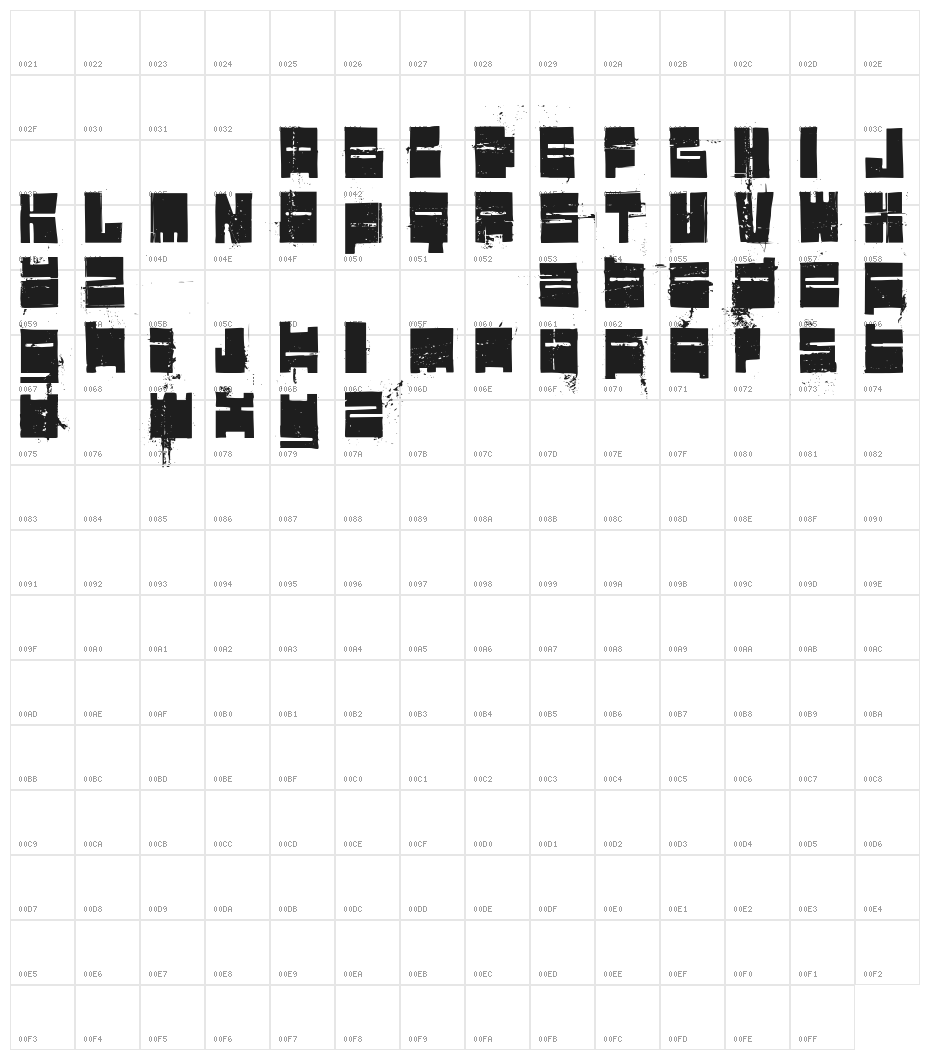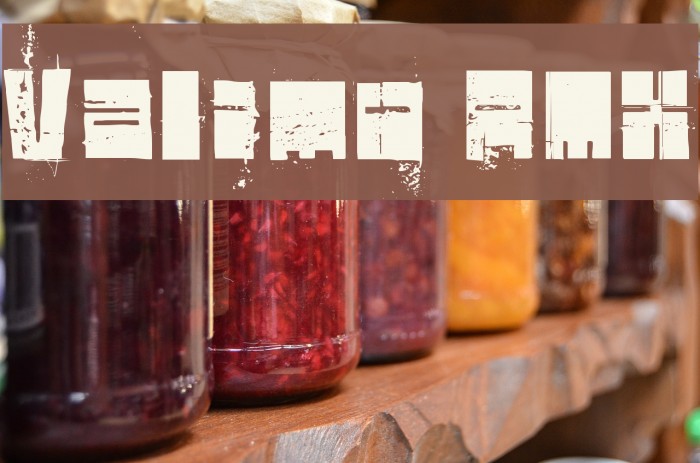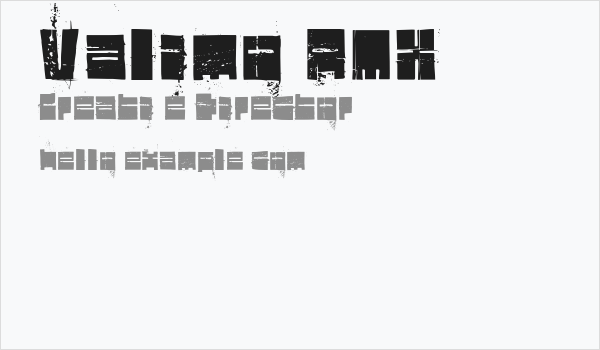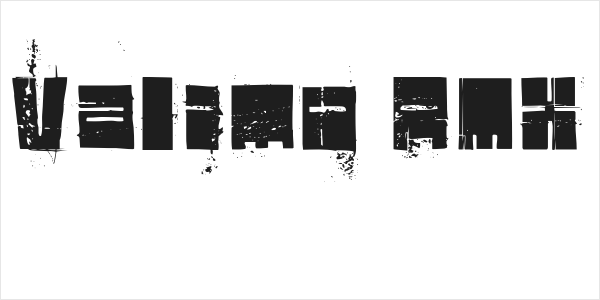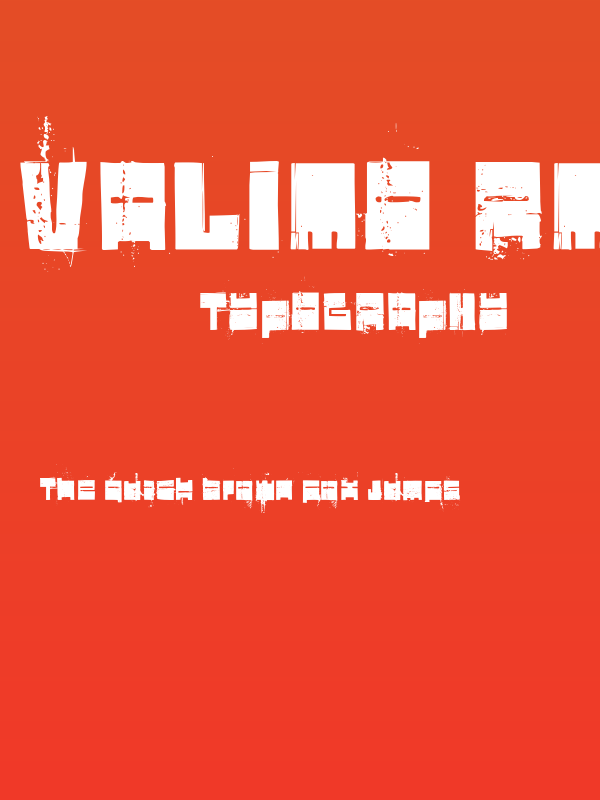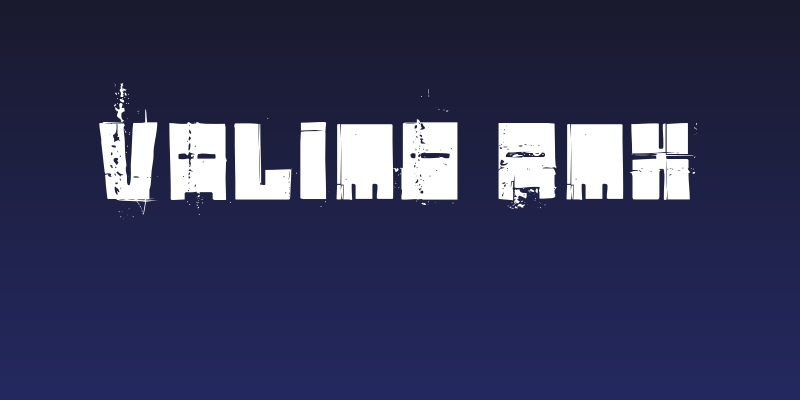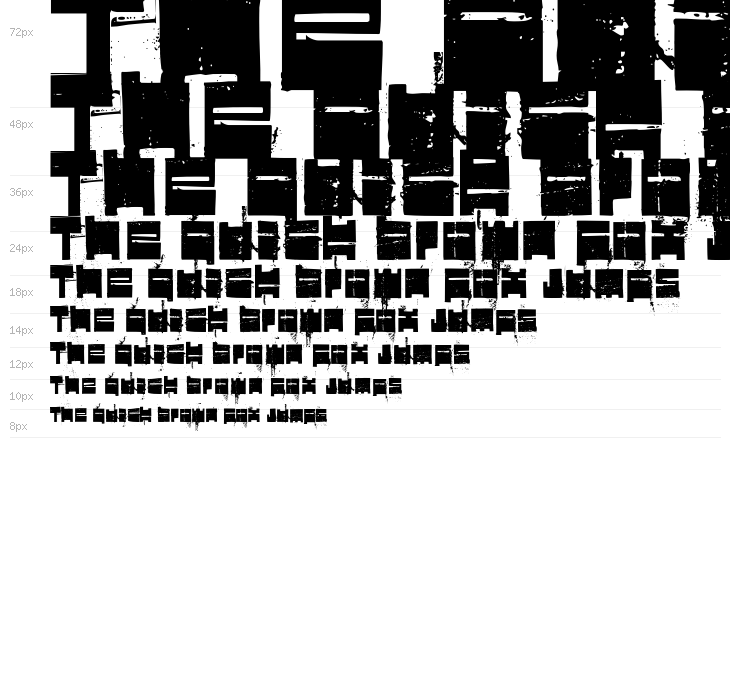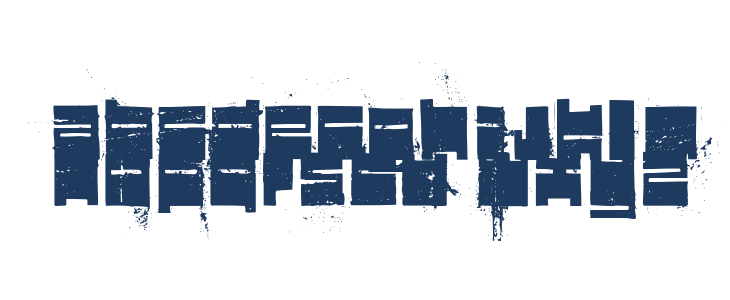
Valimo RMX Font
✎ Distorted Eroded
| Stile generale | Grunge, Urban, Edgy |
| Progetti proposti | Ideal for album covers, posters, streetwear branding, or any project needing a gritty, urban feel. |